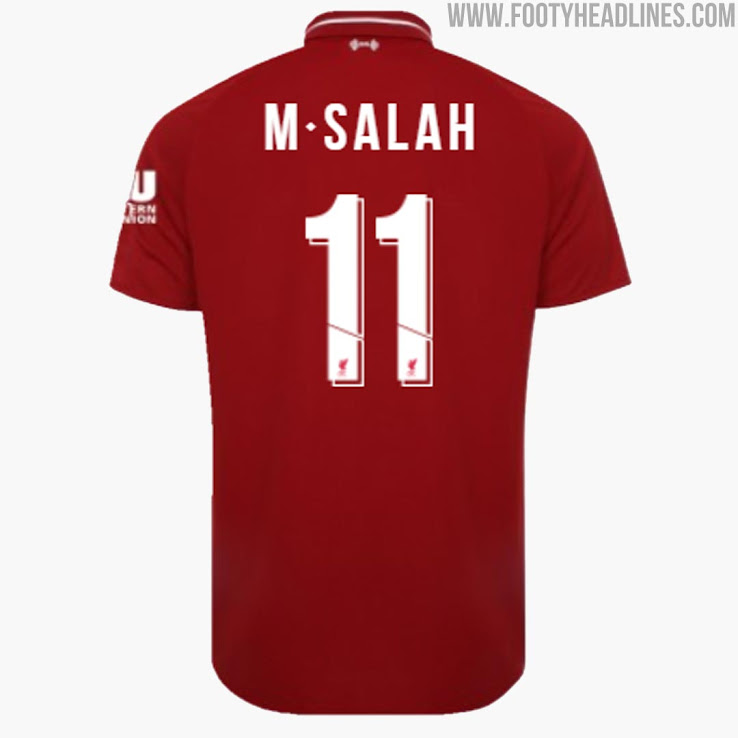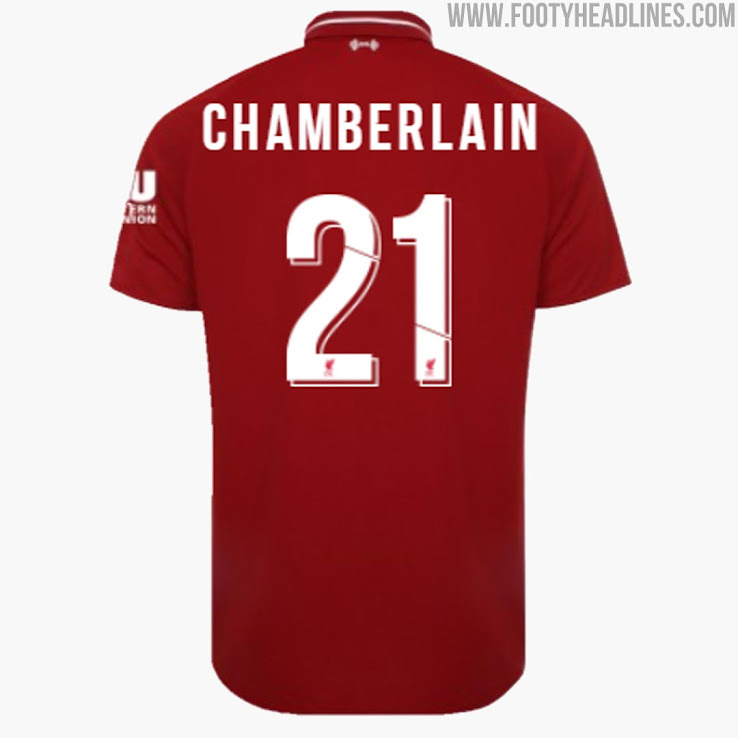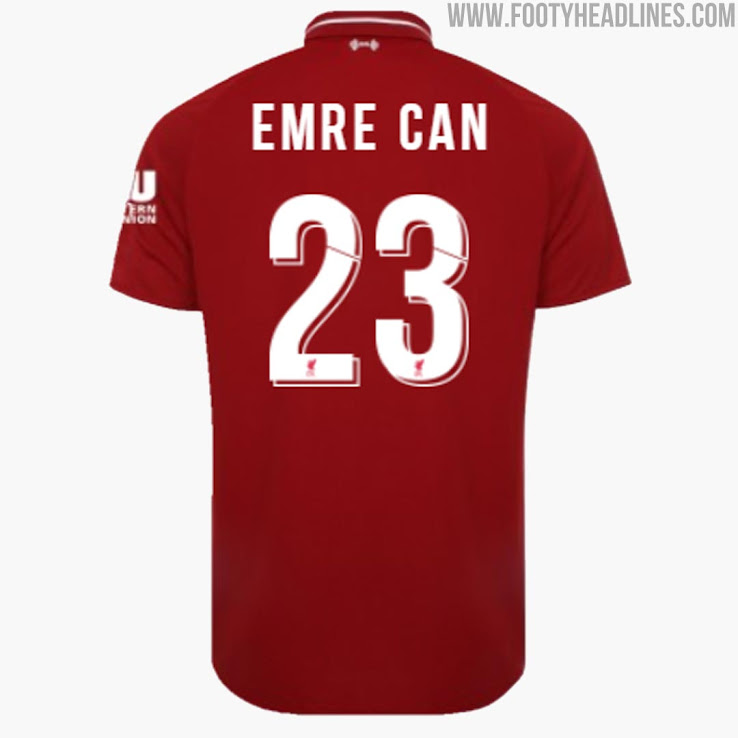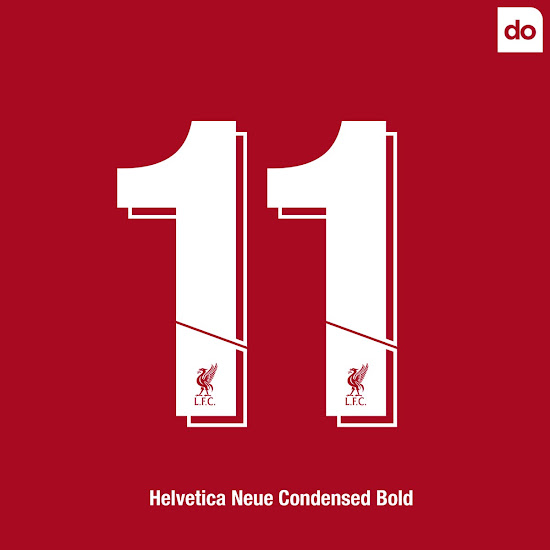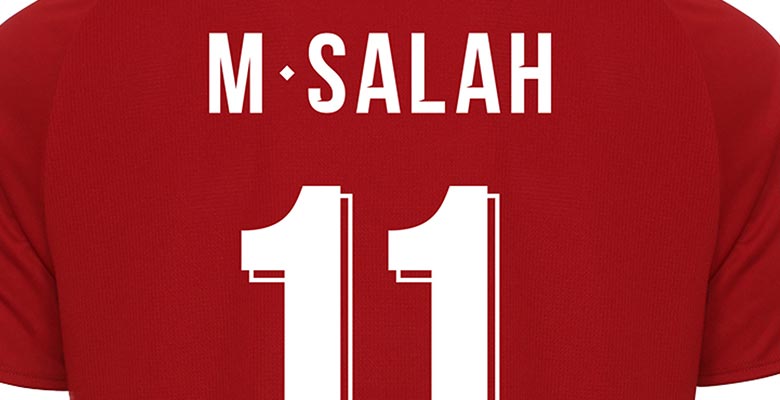
Völlig neue Liverpool 18-19 Trikot-Schriftart enthüllt
Liverpool hat diesen Freitag nicht nur ihr Heimtrikot für die Saison 2018-19 enthüllt, der Klub hat auch eine brandneue, maßgeschneiderte Schriftart für die Saison 2018-2019 präsentiert. Die neue Liverpool 2018-2019 Trikot-Schriftart wird in internationalen Wettbewerben als auch in Pokalspielen verwendet, während der Klub die Premier-League-Schriftart für PL-Spiele verwenden wird.
Liverpool 2018-2019 Trikot - Namen & Nummern
Die neue Liverpool 2018-19 Trikot-Schriftart, die entworfen wurde, um "kultige Charakteristika des Anfield Stadium und des umliegenden Bereichs zu verkörpern", basiert auf der Helvetica Neue Condensed Bold.
Der neue Stil für Namen und Nummern von Liverpools 2018-19 Trikots setzt am unteren Ende auf Liverpools Wappen.